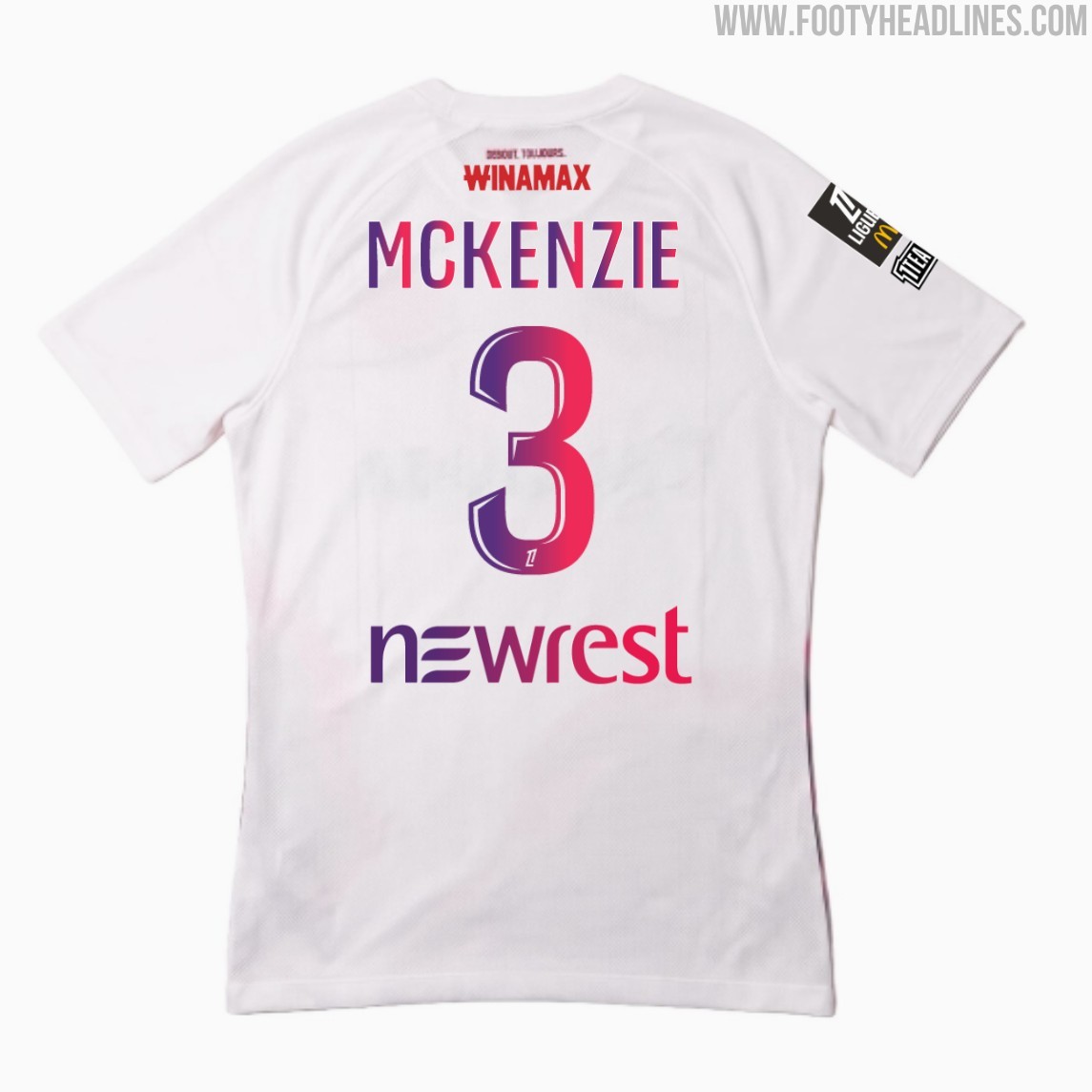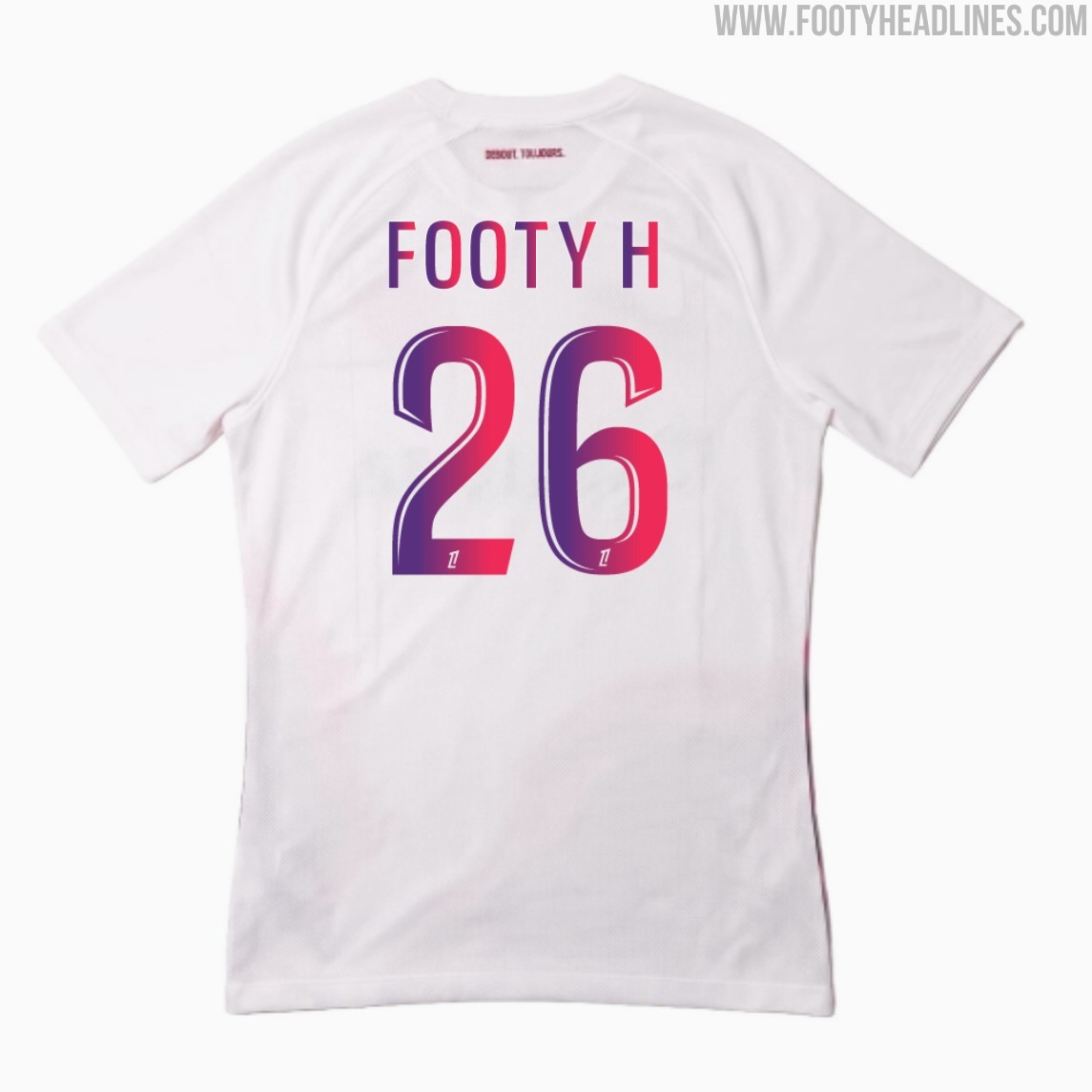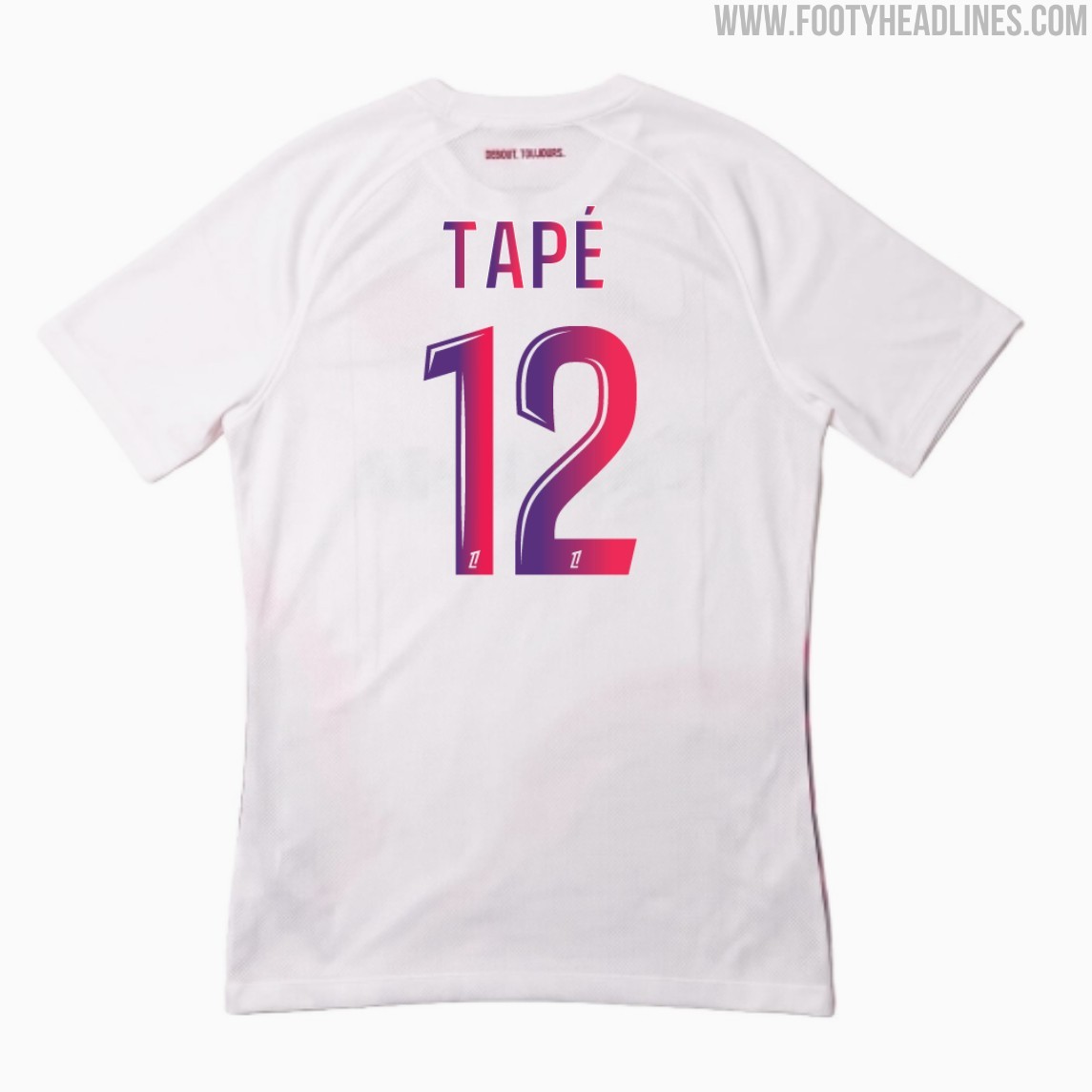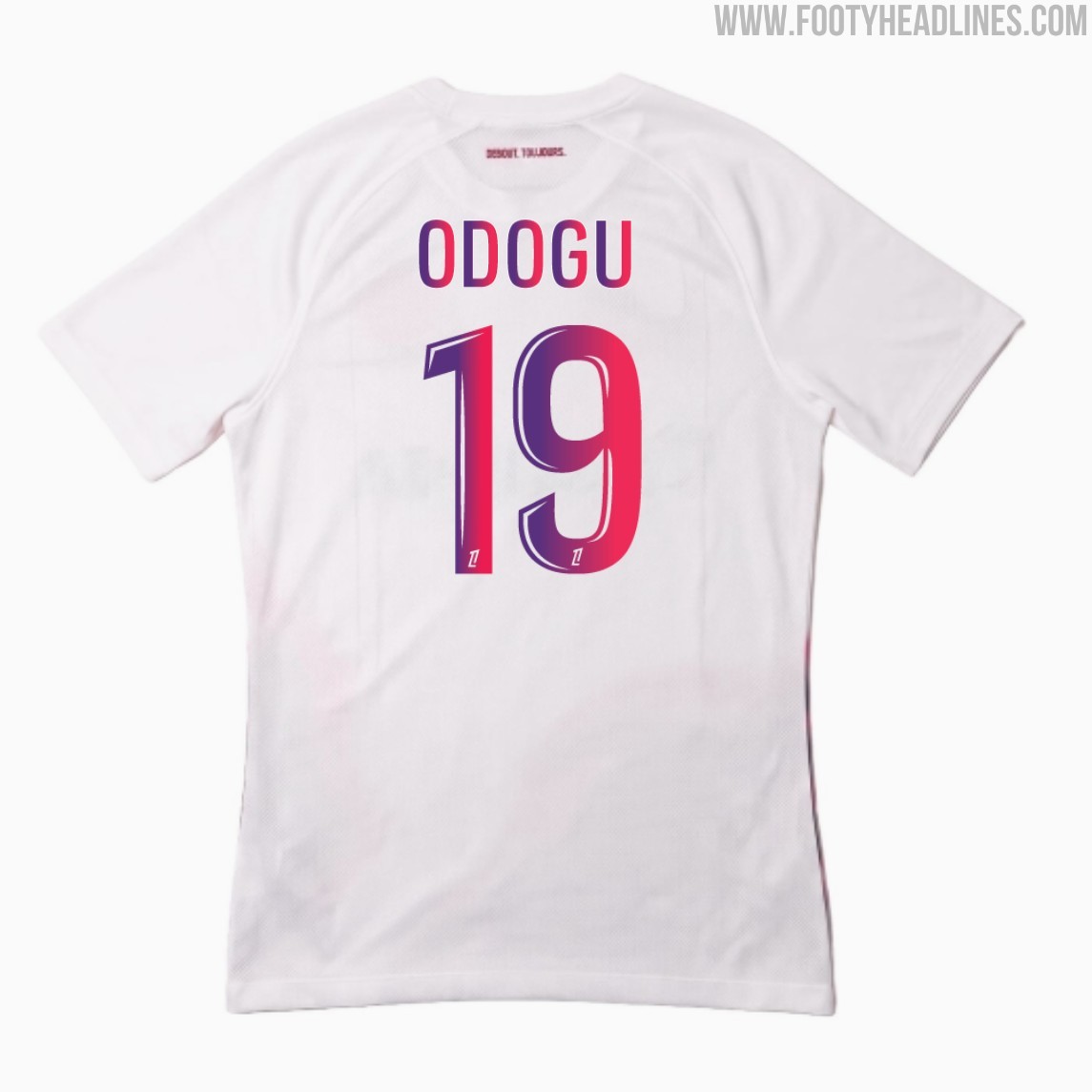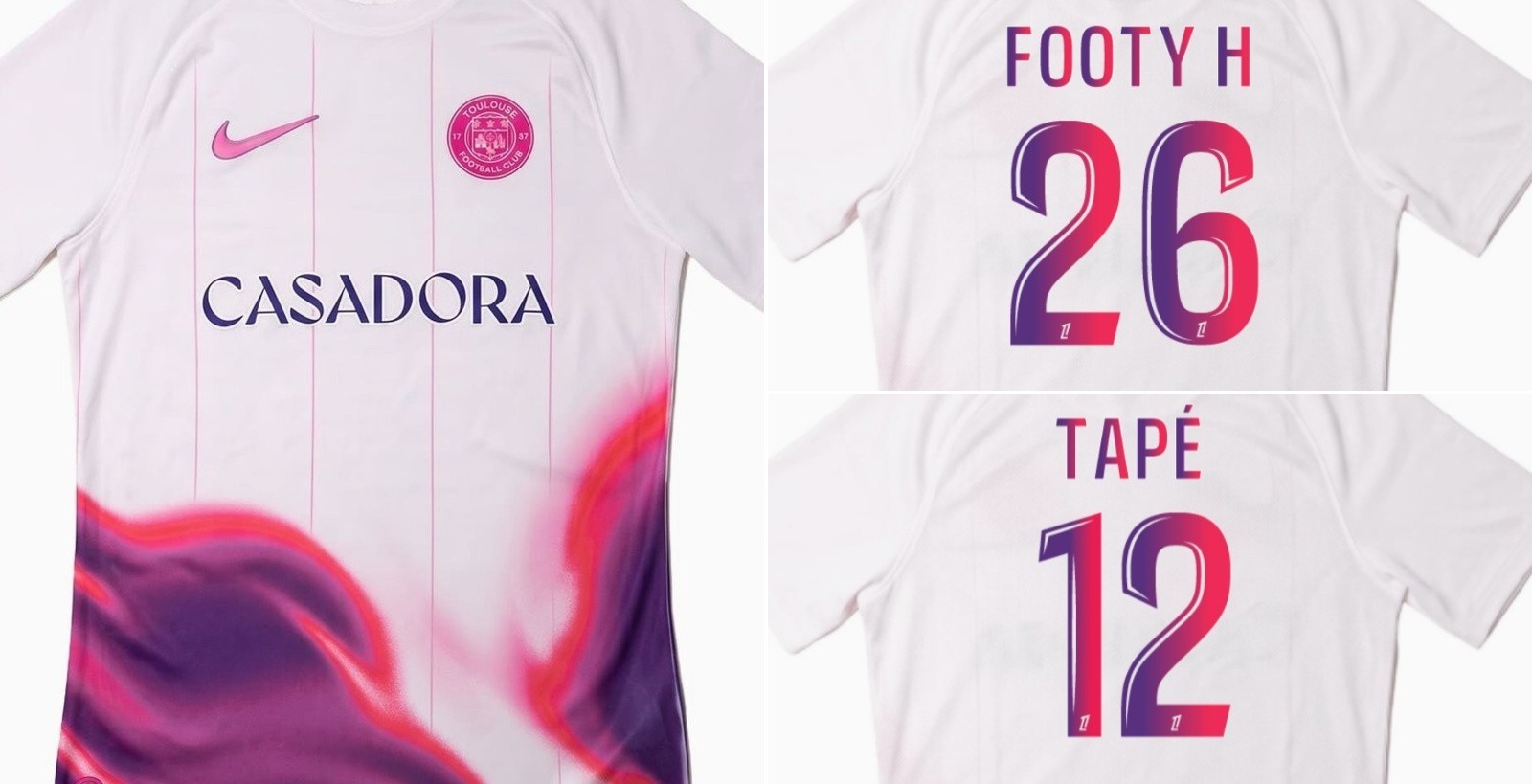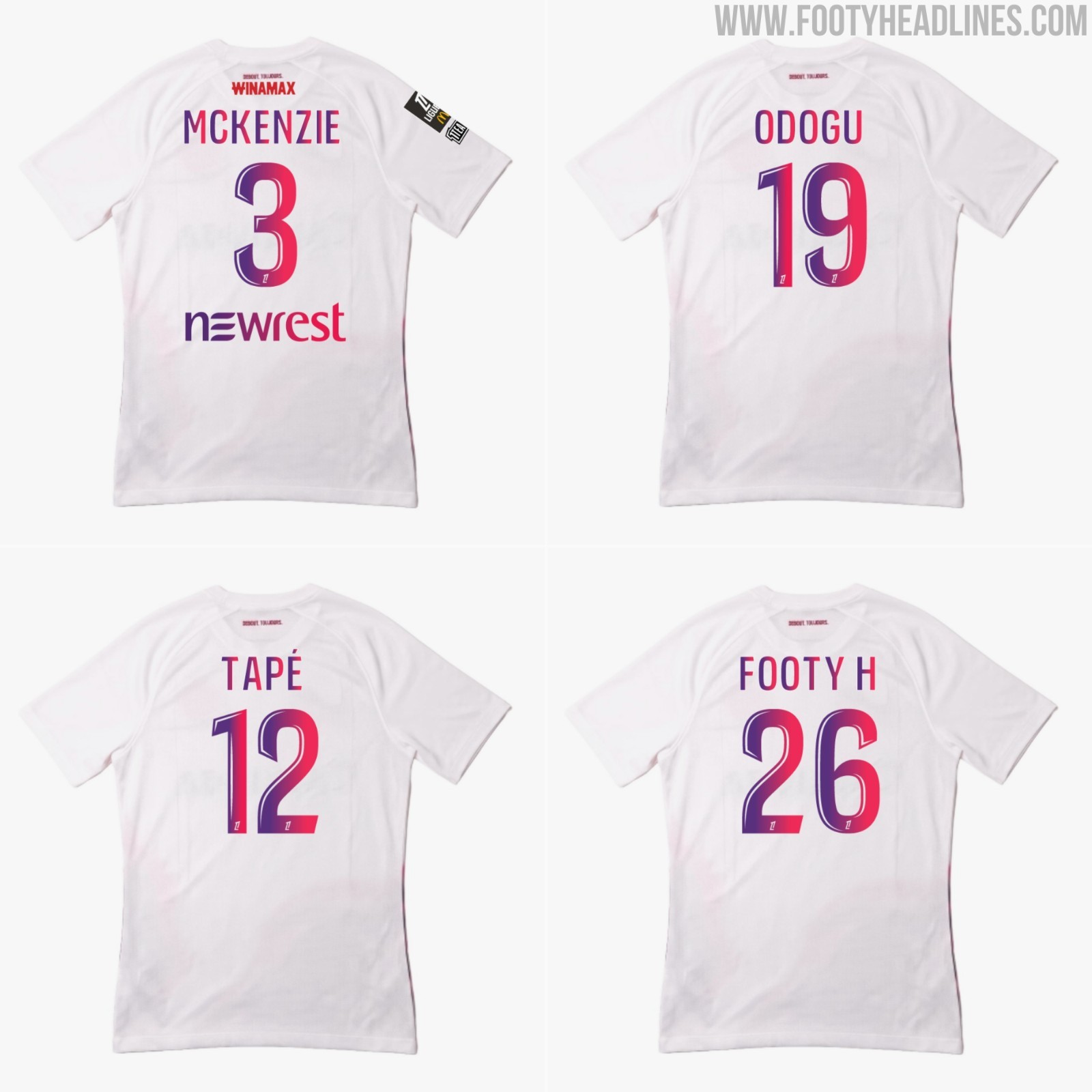
La camiseta visitante del Toulouse para la temporada 26-27 cuenta con una espectacular tipografía personalizada
• Tipografía Personalizada: La camiseta visitante del Toulouse FC para la temporada 26-27 destaca por una tipografía personalizada y vibrante para los números y las letras, presentada por el club y Nike.
• Características del Diseño: La tipografía presenta un llamativo degradado del morado al rosa, contornos redondeados y un monograma en miniatura del Toulouse en la base de cada dígito.
• Aplicación del Degradado: El degradado de color se aplica a cada letra de los nombres de los jugadores por separado, en lugar de al nombre completo, lo cual no es lo ideal.
La camiseta visitante del Toulouse FC para la temporada 26-27 destaca por su llamativa tipografía. En lugar de optar por una tipografía monocromática estándar, el club francés y Nike han presentado un estilo personalizado y vibrante para los números y las letras, diseñado para complementar la estética general de la camiseta.
Tipografía de la camiseta visitante del Toulouse 26-27
La tipografía de la camiseta visitante del Toulouse 26-27 presenta un degradado llamativo del morado al rosa y contornos redondeados. En la base de cada dígito hay un monograma en miniatura del Toulouse, mientras que los nombres de los jugadores en la parte superior de la espalda tienen exactamente la misma transición de color.
Lo que no es lo ideal es que el degradado se aplique a cada letra por separado y no al nombre completo.
En cuanto a la tipografía, la camiseta visitante del Toulouse para la temporada 26-27 utiliza la fuente habitual de la Ligue 1.